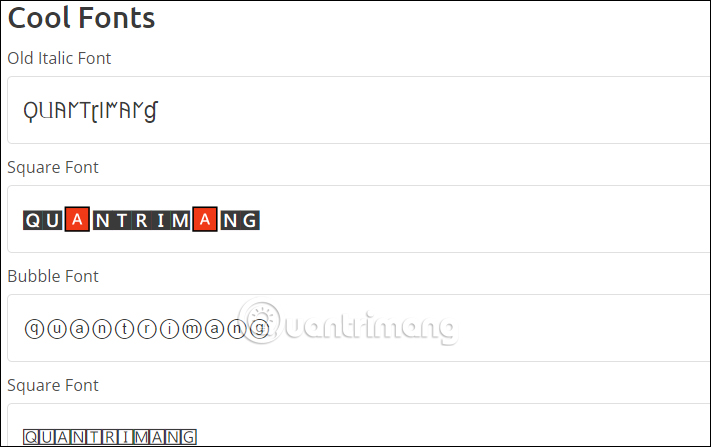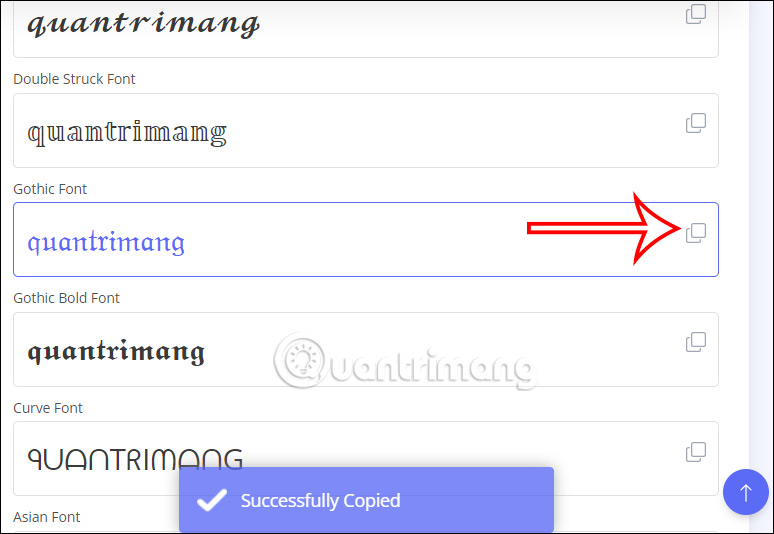
Cách tạo font chữ đẹp, độc lạ trên Font Generator
Font Generator là trang web tạo font chữ đẹp để bạn đăng status hay sử dụng cho những mục đích khác, mang lại cái nhìn mới mẻ hơn cho nội dung. Bạn có thể dùng Font Generator để tạo font chữ cho Instagram hay viết chữ kiểu trên Facebook với chữ nghiêng, chữ gạch ngang,... Bạn chỉ cần lựa chọn kiểu font muốn dùng rồi nhập chữ để tạo là được. Bài viết dưới đây sẽ hướng dẫn bạn dùng Font Generator tạo font chữ đẹp.
Hướng dẫn dùng Font Generator tạo font chữ đẹp
Tiếp đến bạn nhập nội dung muốn tạo font chữ đẹp của mình vào khung Enter your text here trên trang web Font Generator.
Nhập nội dung trên Font Generator
Ngay sau đó ở bên dưới bạn sẽ thấy các mẫu font chữ đẹp, nghệ thuật hay độc lạ để chúng ta lựa chọn sử dụng.
Mẫu font chữ trên Font Generator
Người dùng có thể sử dụng thanh Preview size để phóng to chữ hơn và xem font chữ nào phù hợp với nhu cầu sử dụng của mình.
Phóng to font chữ trên Font Generator
Khi ưng ý font chữ đẹp nào tạo trên Font Generator, bạn chỉ cần nhấn vào biểu tượng copy ở từng dòng chữ để sao chép và dán sang nội dung khác là được.
Copy font chữ trên Font Generator